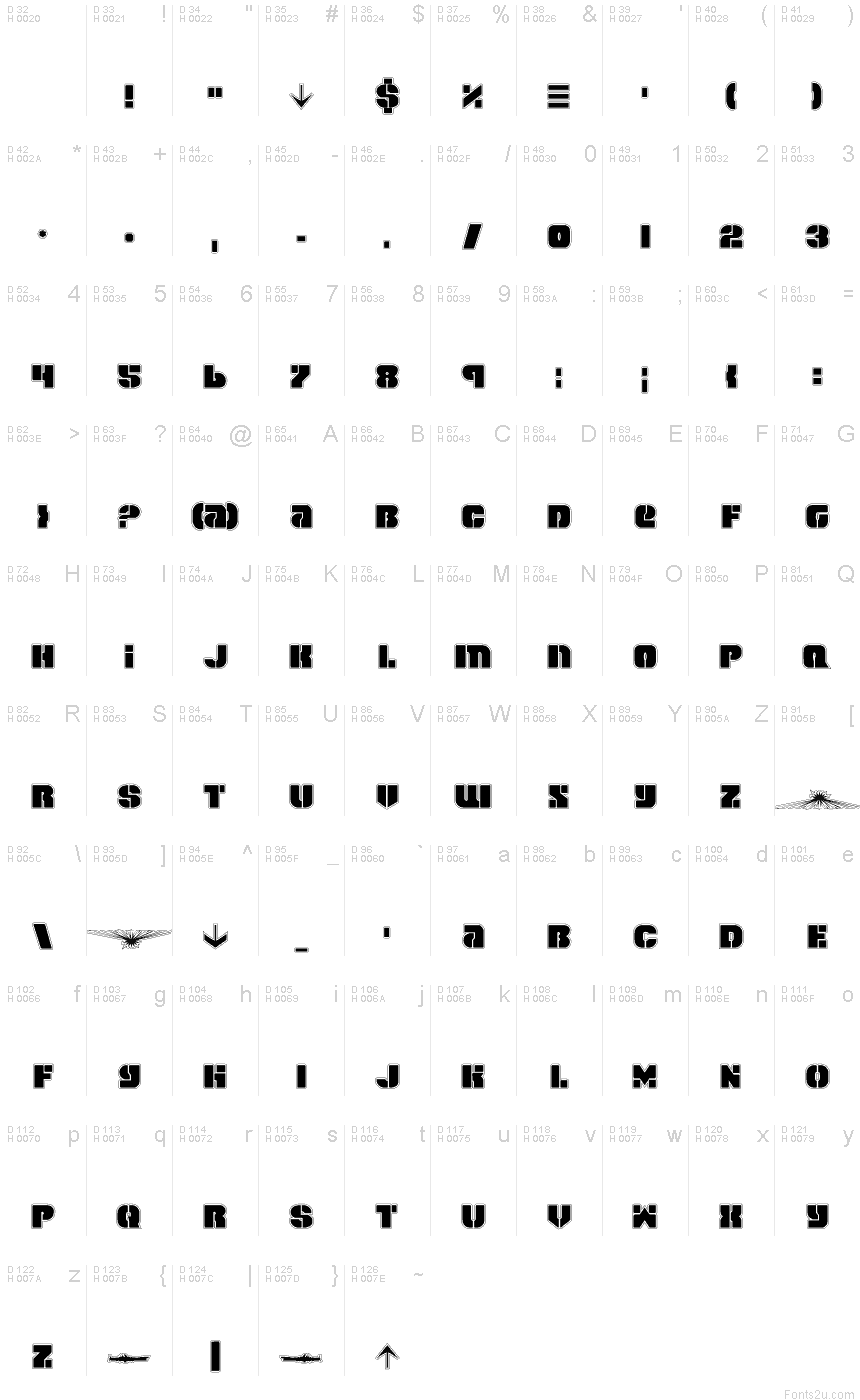
Space Cruiser Pro od Iconian Fonts to darmowy, futurystyczny krój display, wyróżniający się masywną sylwetką w stylu ery kosmicznej oraz zaokrąglonymi rogami, które przywodzą na myśl automaty do gier i opakowania klasycznej fantastyki naukowej. Litery są szerokie i kompaktowe, z kwadratowymi wycięciami, miękkimi łukami i podwójnym obrysem, co nadaje czcionce charakterystyczny, tłoczony wygląd godła, zamiast gładkiego, chłodnego stylu high-tech.
Świetnie sprawdza się w tytułach plakatów, logotypach gier, okładkach komiksów, opakowaniach zabawek czy planszach tytułowych, wszędzie tam, gdzie krótkie hasła potrzebują retro-kosmicznego impulsu. Jako darmowy font, doskonale nadaje się również do ulotek klubowych, nagłówków na YouTube i monogramów, zwłaszcza gdy chcesz, aby wielkie litery wyglądały jak emblematy, a nie zwykły tekst.